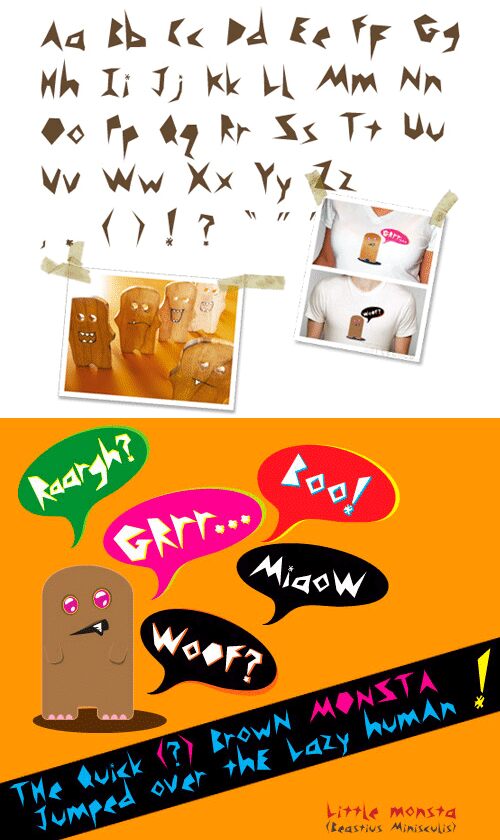
Monsta von Olivier Perkins ist eine kostenlose, eckige Display-Schrift, die aus scharfen, aufgebrochenen Silhouetten aufgebaut ist. Ihre Buchstaben kombinieren breite Keile, abrupte Diagonalen und unregelmäßige Aussparungen, wodurch eine spannungsvolle Form entsteht, die eher an grafische Scherben als an konventionelle Schrift erinnert. Jede Form weist eine spitze Kante auf.
Plakatdesign ist ihr stärkstes Anwendungsgebiet, besonders für experimentelle Musik und Horror-Events. Die strenge Geometrie passt zudem gut zu Merchandise für Monstergeschichten und futuristische Spiele. Albumcover und Spiel-Titelkarten erhalten durch die gebrochenen Formen eine passend aufgebrochene Oberfläche, besonders in Kombination mit Collage, eckiger Illustration oder kontrastreicher Fotografie.